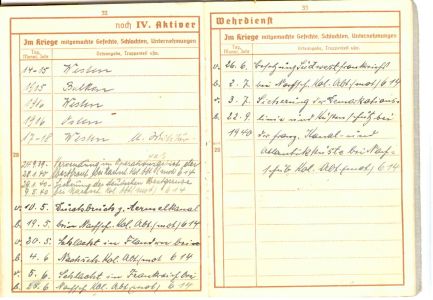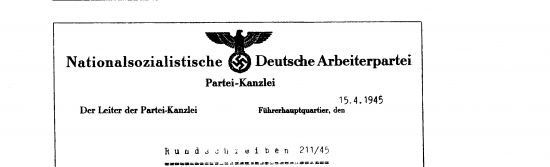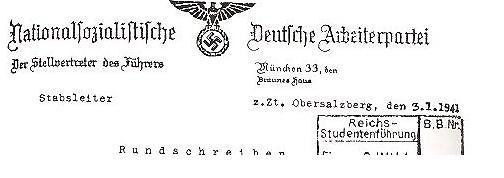
Schrift im Nationalsozialismus
Nochmal zurück zur eigentlichen Frage;
1933-45
Gebrochene Schriften (Fraktur, Schwabacher)
Antiqua
Grotesk
Handschriftliches: Kurrentschrift (Sütterlin)(1)
Schreibmaschinenschriften
ab 1941
Verbot der "Judenlettern" (Gebrochene Schriften) aufgrund des Führererlasses von 1941, danach sollte die sogenannte Deutsche Antiqua(2) von offizieller Seite her eingesetzt werden.
zu 1)
Gab es zu dieser Zeit (und auch schon davor) eine von der Antiqua abgeleitete Handschrift, die in Schulen unterrichtet wurde?
Soweit ich mich erinnere, hat mein Urgroßvater in seinem Physikheft von 1924 für seine Notizen und Bemerkungen keine Kurrentschrift verwendet, sondern eine handschriftliche "Antiqua". Die Briefe seiner Frau sind aber in Sütterlin geschrieben...
zu 2)
Ist dies nur ein allgemeiner Begriff für Antiqua?
Oder eine spezielle Schrift?
Gibt es Beispiele (Web, Bücher)?
Falls faktische Fehler im Text vorkommen, bitte korrigieren.
Um noch einmal zu verdeutlichen, was ich meine: Wenn man wie ich hauptberuflich mit Büchern (aus dieser Zeit) zu tun hat, wird man mit der Zeit feststellen, dass die allenthalben propagierte These, die Fraktur sei die völlig dominierende – ja einzige – Schrift in Deutschland zwischen, sagen wir, 1910 und 1933 gewesen, arg relativiert werden muss. Und ich gebe Dir völlig recht: eine klare politische Zuordnung lässt sich dabei nicht ausmachen. ‹Rechte› und ‹linke› Verlage benutzen und mischen beide Schriften, wobei – dies der Eindruck aus meiner Erfahrung – für fiktionale Literatur tendenziell mehr Fraktur verwendet wurde, für Sachtexte (so habe ich Spengler bezeichnet, im Sinne von ‹nicht-fiktionale Texte›) tendenziell mehr Antiqua. Diese bescheidene Beobachtung würde ich weiterhin vertreten wollen.
Ad Rowohlt: Dass die Gebrüder Jünger, von Salomon und andere bei Rowohlt veröffentlichten, ist zweifellos richtig. Berühmt wurden Ernst Rowohlt und Kurt Wolff jedoch mit ihrem frühen Einsatz für – pardon – ‹linke› Autoren wie Heym, Tucholsky, Kafka, Musil, Brod, Ball, Arnold Zweig etc.
Es ist unnötig, daß Du ein solches Faktum als "bescheidene Beobachtung" ausweist - aber es ziert Dich :-)
Linke, Rechte - ja, ich weiß schon. Wo hat Ernst Niekisch publiziert? Auch bei Rohwolt? Er war in dieser Zeit Anhänger des Nationalbolschewismus. Es ging mehr um Nationales Denken und Internationalismus, weniger um Links und/oder rechts. Dieser Schreiberling Arnold Bronnen - publizierte bei Rowohlt. "O.S." in einer für die damalige Zeit neuen Art des Schreibens. Gedruckt in Fraktur. War er links oder rechts. Beides, je nach Jahreszeit. Rechte, Linke - egal. Hauptsache national. Oder was ist mit A.Paul Weber? Hat er nicht für Autoren aller Richtungen gearbeitet? Ich liebe seine Arbeiten.
Ich habe wegen des "Führer-"Erlasses von 1941 bezüglich des Frakturverbotes gerade einmal nachgeschaut. Sämtliche Militärunterlagen meines Vaters und meines Großvaters mütterlicherseits, also Wehrpaß, Lazarett-Bescheinigungen, Auszeichnungen.. alles auf vorgedruckten Formularen in Fraktur dargestellt. Da hat der Erlaß des "Führers" wohl bei der Wehrmacht keinen sonderlichen Eindruck hinterlassen.
Ergänzung:
Hier ein Auszug aus dem deutschen Wehrpaß.
Ein deutsches Leben auf einer DIN A7 Seite.
Vor 1933 schrieb sich die Familie meiner Mutter André.
Der Akzent tegue ging dann 1933 irgendwie verloren. Joh.
Hier mal der Originalbriefkopf des Verbotserlasses.
Seltsamerweise noch in einer gotischen Schrift gesetzt.
Darunter zum Vergleich nach der Umstellung.
Ich vermute, daß die zeitgleiche Umstellung aller Druckerzeugnisse auf Antiqua-Schrift aus wirtschaftlichen (kriegsbedingten) Gründen nicht erfolgen konnte.
Daher wurden nzunächst alle vorhandenen Reserven aufgebraucht und der Verbotserlaß erst bei einer Neuauflage von Drucksachen beachtet
Ich habe eine Schulchronik von Zwittau, Mähren wo bis Ende 1941 alle Einträge in (deutscher) Kurrentschrift vorgenommen sind und ab Beginn 1942 richtig auffallend ausschließlich mit (lateinischer) Schreibschrift fortgefahren wird.
Nicht dass dies meine alltägliche Lektüre wäre: Aber im «Völkischen Beobachter» ist sehr gut zu sehen, wie nach 1941 wirklich schrittweise und systematisch der Lauftext von Artikeln auf Antiqua umgestellt wird. Wie steht es aber eigentlich mit Anzeigen? Ich habe den Eindruck, dass hier weder vor noch nach dem ‹Edikt› eine Beschränkung oder Vorgabe bestanden hat.
Leider kann ich keine Quelle nennen. Aber ich habe gelesen, daß das Frakturverbot nur für die amtlichen Verlautbarungen galt. Wobei es zur damaligen Zeit eine völlig andere Presselandschaft in Deutschland gab als heute. Sehr wohl gabe es Presse-Zaren wie Hugenberg. Aber außerhalb der Großstädte kämpften viele kleinere Zeitung täglich um die Inserenten und damit ums Überleben. Hans Fallada schrieb in seinem Roman "Bauer, Bonzen, Bomben" sehr spannend und interessant darüber. Die fiktive Geschichte beruht auf eine tatsächlich erschienene kleine Zeitung, die u.a. eben von den öffentlichen Verlautbarungen lebte, die bezahlt wurden.
Was die Verwendung der Bernhard-Fraktur vor 1941 beim Völkischen Beobachter angeht, so gibt ein Detail der Sache sicher noch ein wenig Würze: Lucian Bernhard war ein Künstlername. Sein richtiger Name lautete Emil Kahn und er war Jude. Das war diesem NSDAP-Organ sicher mehr als peinlich.
Die "Grabkreuze" im Massengrab mit der Inschrift "Ils n'on pas passé" stammen passenderweise aus Beständen einer englischen Buchdruckerei. Wozu die wohl soviele deutsche Eiserne Kreuze gebraucht hatten?
der Tagesbefehl in einer Antiqua.
Lese ich da »4. November 1914, vrtmittags«?